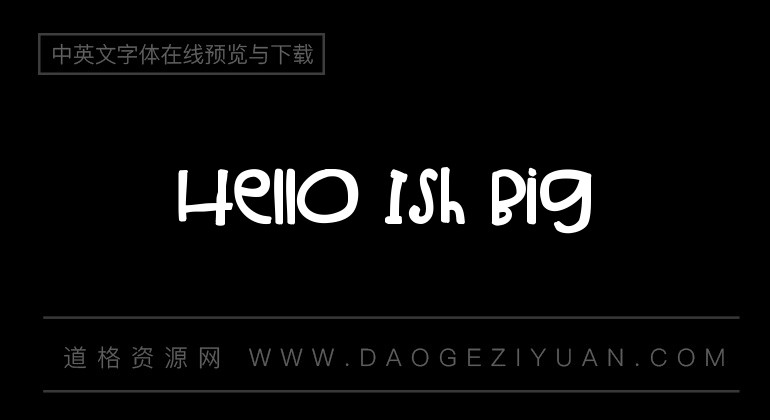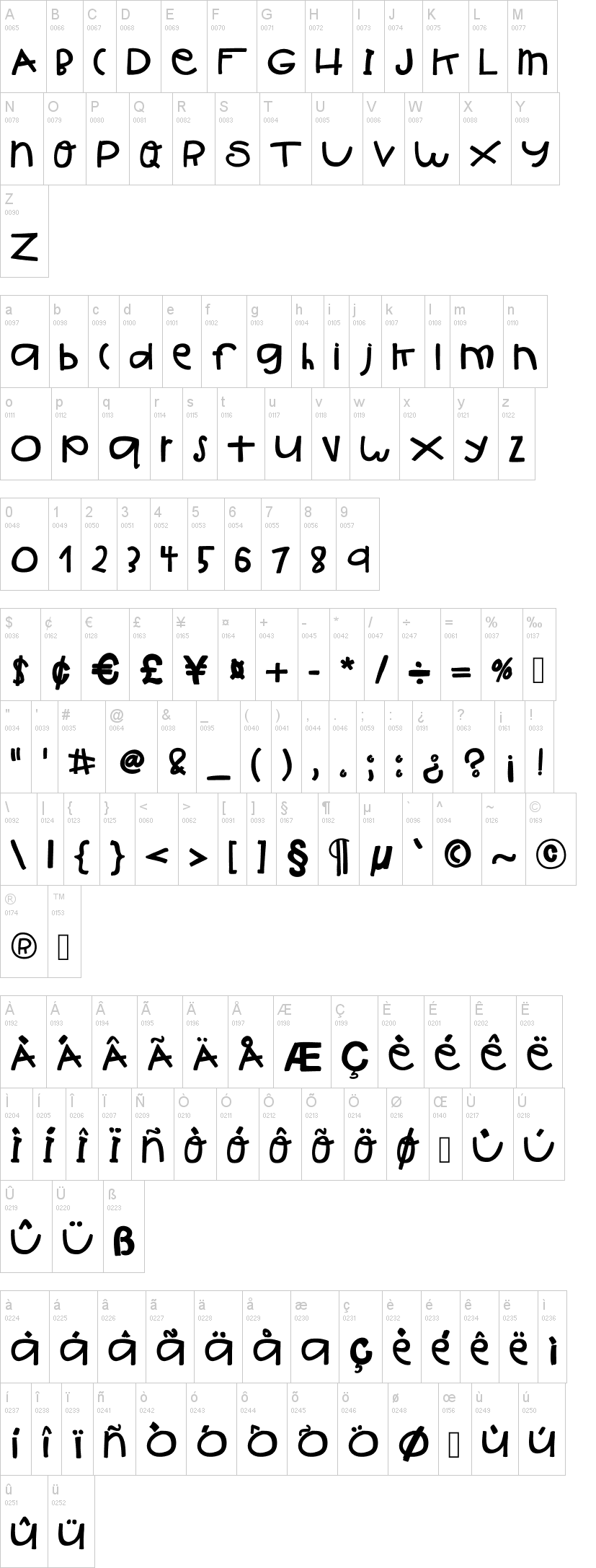
Hello Ish Big
Hello Ish Big是一款非常特别的字体,它是由著名设计师Ish Big创作的。它的特色是有着温暖的感觉,并且具有自然的曲线和抽象的形状。它的字体大小为20px,可以用于制作海报、标志、标题等设计。它的字体特征是结构紧凑,能够提供清晰的文字效果。它也可以被用于网页设计,可以提供更加舒适的视觉效果。
Hello Ish Big是一款非常不错的手写艺术字体,具有很好的视觉感,适合于文化类的宣传设计、商业类品牌的广告和产品包装设计以及个性化文字排版等较多场景。